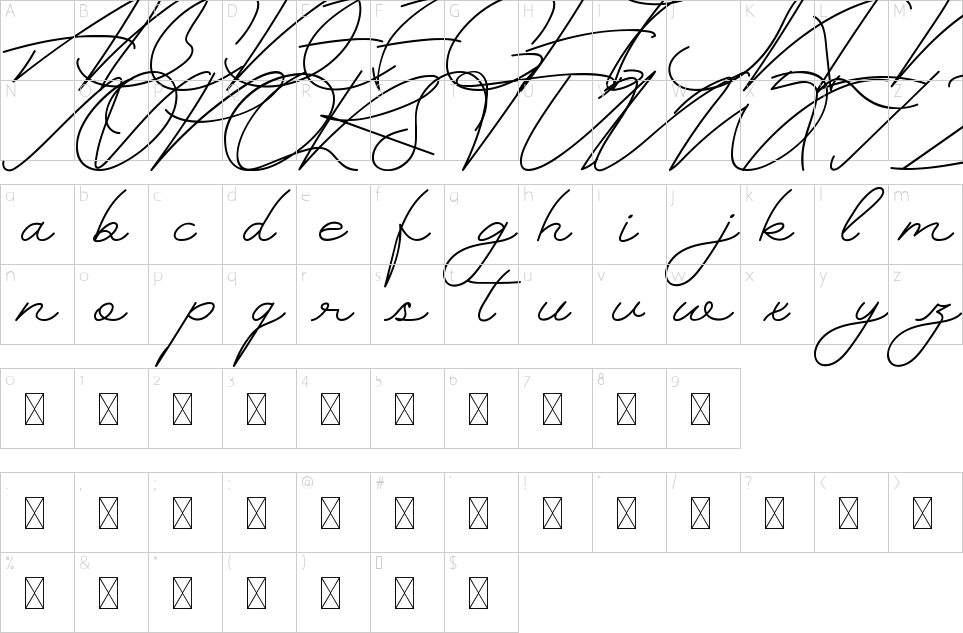
Descubra a elegância da Plularius Font para seus projetos digitais com esta oferta gratuita do CalligraphyFonts. Esta font é perfeita para adicionar um toque único e autêntico às suas criações, seja para textos legíveis ou design gráfico sofisticado. Desenvolvida pelo incrível talento da equipe de designers de letras, a Plularius Font oferece uma variedade de estilos que vão desde linhas finas até mais espessas e detalhadas. Seja você designer gráfico, jornalista ou criador de conteúdo digital, esta font é uma excelente escolha para aqueles buscando um estilo autêntico e versátil. A Plularius Font tem sido baixada 2.976 vezes pelo público global, mostrando a sua popularidade e qualidade. É essencialmente gratuita para o uso pessoal, permitindo-lhe explorar todas as suas capacidades sem limitações comerciais. Descubra agora essa font única e personalizável que enriquece seus projetos com um toque de sofisticação e individualismo.